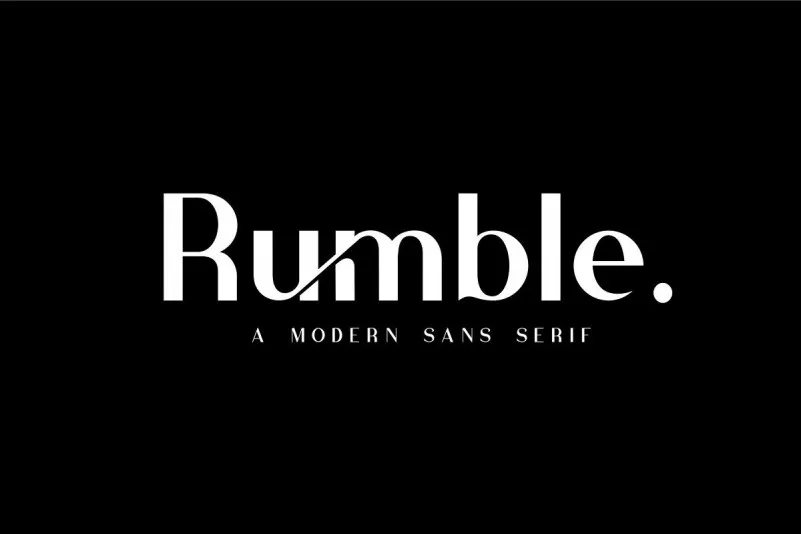
Rumble Modern Sans Font – Download Grátis
Esta é uma fonte sans-serif moderna. Representada por letras minúsculas estreitas e maiúsculas alongadas. Para obter um design elegante e contemporâneo, combine-as juntas. Introduzimos a Rumble Font! Ela foi projetada e compartilhada pela Hanzel Studio. Combina elegância nas letras para fazer esta fonte parecer exclusiva e elegante. Com letras altas bem definidas e finas na anatomia de cada letra, é um tipo de sans-serif incrivelmente bonito que é ao mesmo tempo elegantemente clássico e moderno por natureza. Crie cartões de convite para casamentos belos, use-a como uma solução elegante para sua próxima layout de revista, ou escolha Rumble para qualquer gráfica que exija um look atraente com um toque vintage. Baseada em letrinhas clássicas para publicação e gráficos de destaque, você pode dar ao seu texto uma sensação elegante e clássica usando as linhas limpas e contrastantes da Rumble e os estilos alternativos finos e grossos. Esta descrição convida o leitor a explorar as possibilidades criativas do tipo de letra Rumble Modern Sans, destacando sua funcionalidade para várias aplicações gráficas modernas e elegantes.